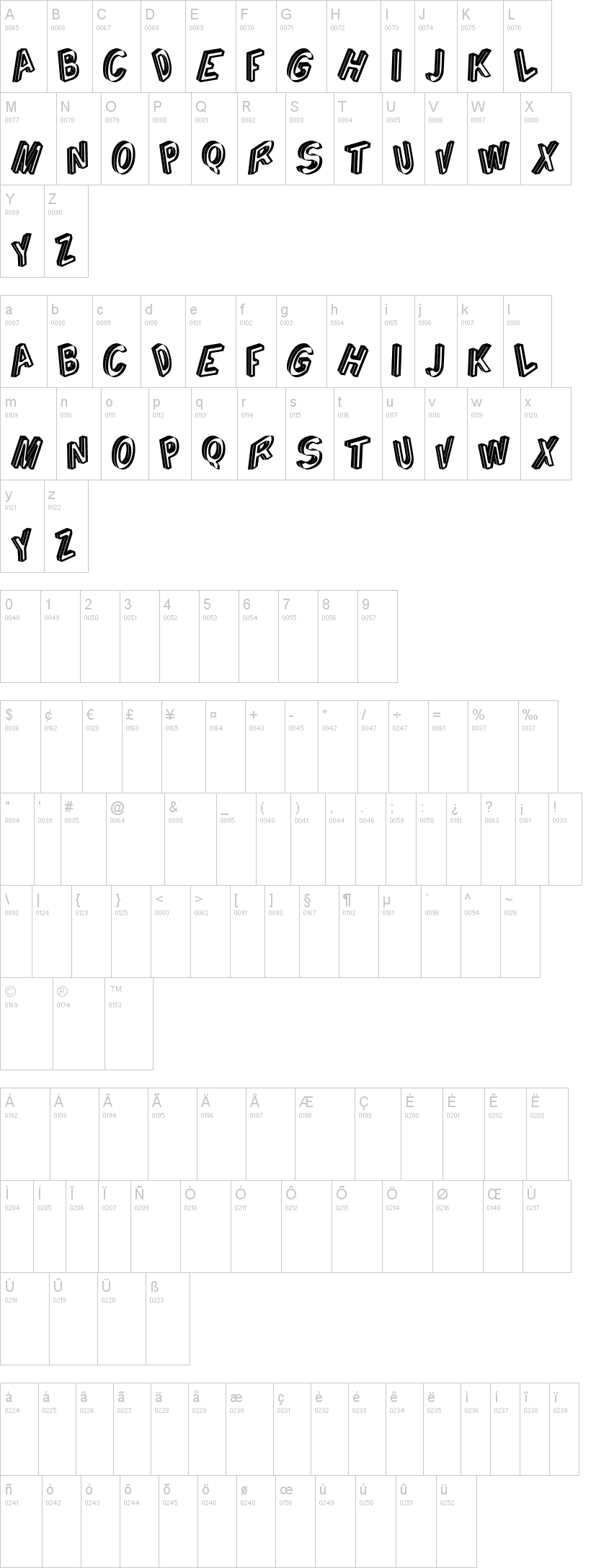
Cargante TFB
Cargante TFB 是一款新型的多功能字体,它是由西班牙设计师Oscar Yanez设计的。字体的特点是拥有清晰的轮廓,清晰的笔画,易于阅读的字体,适合用于文本和标题。它还具有一定的灵活性,可以根据不同的需求进行调整,使用户可以根据自己的喜好调整字体的大小,以及字体的风格和外观。Cargante TFB字体也可以用于网页设计,以及图标设计等。
Cargante TFB是一款非常不错的手写艺术字体,具有很好的视觉感,适合于文化类的宣传设计、商业类品牌的广告和产品包装设计以及个性化文字排版等较多场景。
Cargante TFB字符映射图